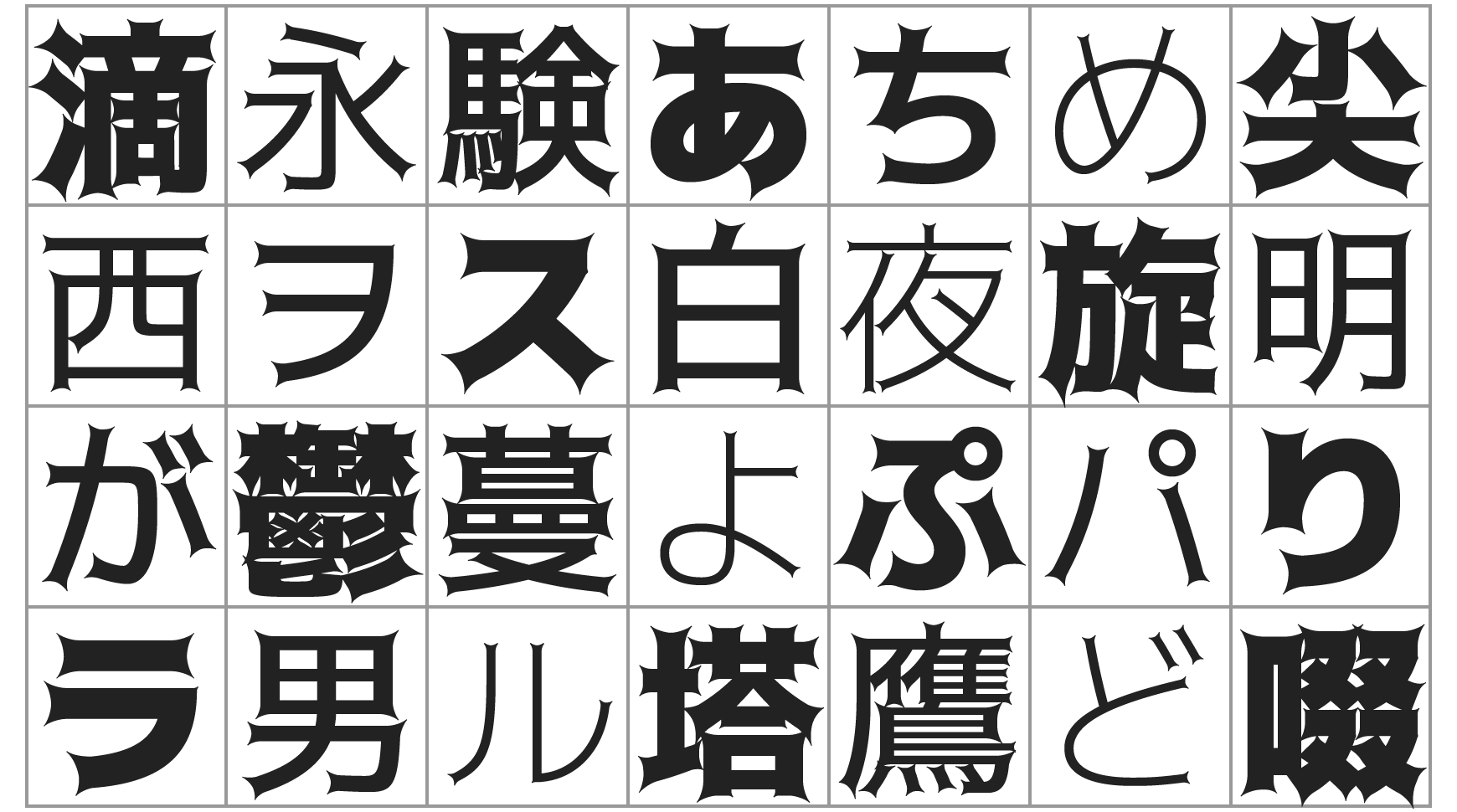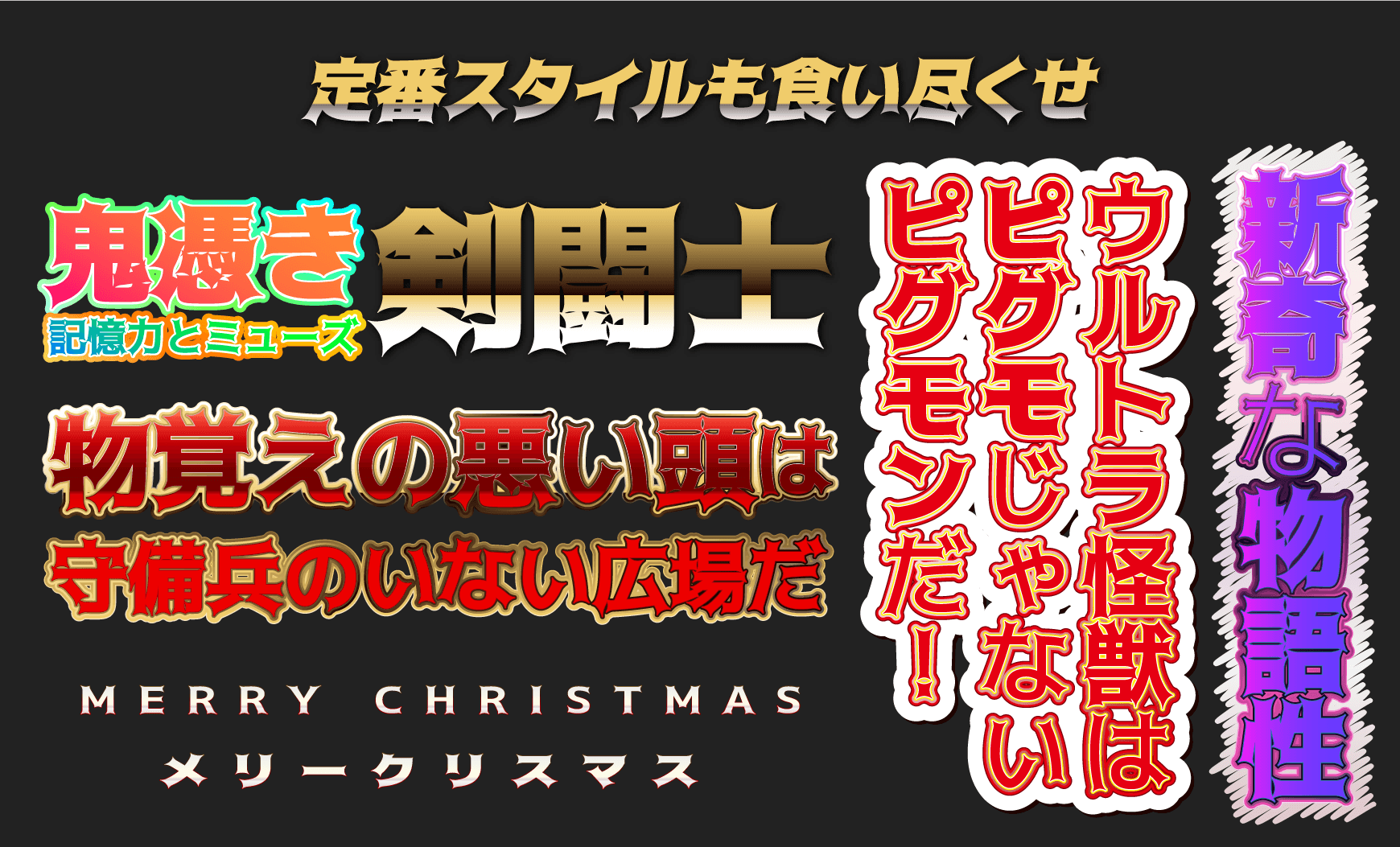
托加里特体(トガリテ):充满魔幻魅力的个性字体
「 托加里特体 」 (日文名:トガリテ) ,英文名称 togalite 。这是一款充满魔幻魅力的日系字体,是基本开源字体 「 M+ FONTS 」 进行开发的字体。虽然是一款日系的字体,但是收录的汉字多达5300个, JIS第1水准(2965字),JIS第2水准(2257字) 。主要繁体中文较多,简体中文也部分支持。这款字体特别适合做机甲风,魔幻风的设计,字体比较有特色,是值得推荐的一款字体。
托加里特体(トガリテ):充满魔幻魅力的个性字体-1
托加里特体(トガリテ):充满魔幻魅力的个性字体-2
托加里特体(トガリテ):充满魔幻魅力的个性字体-3
托加里特体(トガリテ):充满魔幻魅力的个性字体-4